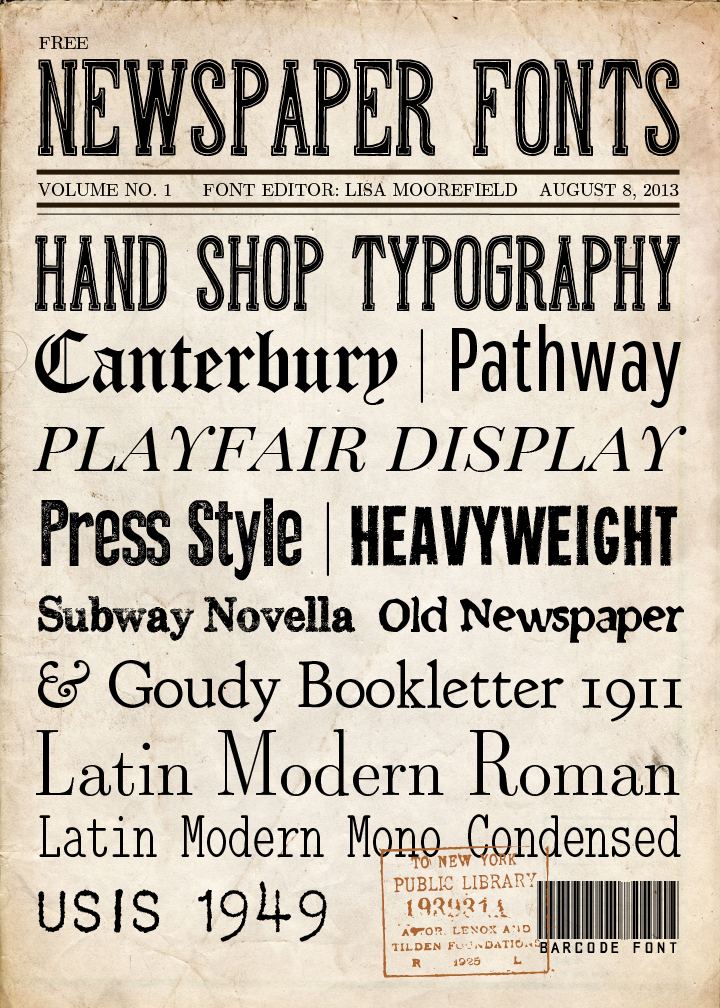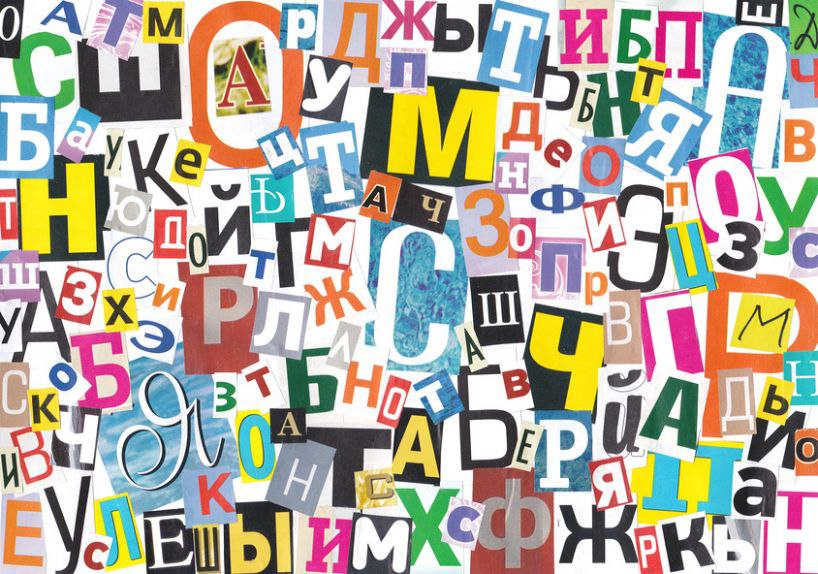
Шрифт в печатном издании | Полиграф-Сити
Г. М. Барышников, художник-шрифтовик
Даже неискушенному читателю ясно, что нельзя использовать в наборе стихотворных произведений шрифты, которыми набираются газеты или словари, а в газетах или словарных изданиях — шрифт для набора искусствоведческой литературы, так же, как в детских изданиях — шрифты для рекламы и акциденции.
Шрифт недаром считается одним из важнейших средств художественного оформления любой печатной продукции. При выборе шрифта для набора любого типа издания профессиональный издатель прежде всего учитывает его функциональные и художественно-эстетические особенности, а также удобочитаемость и психофизиологию восприятия. Один шрифт разработан специально для длительного чтения, и им набираются книги.
Другой — для энциклопедий и словарей, и ни в каком другом типе издания, в силу характера своего рисунка, расположения знака на кегельной площадке и его очка, не может быть использован.
Третий, изначально созданный для набора букварей, учебников младших классов и детской литературы, непригоден для применения в газетах или журналах.
Но всегда ли это происходит не самом деле? Наверное, каждому доводилось неоднократно сталкиваться с таким явлением, когда интересная по своему содержанию книга читается с трудом. Вы испытываете какой-то дискомфорт, с нарастающим раздражением, спотыкаясь на каждой строке, с трудом одолеваете очередную страницу и не понимаете, отчего не плучается осилить всего 10-12 страниц за раз.
Массовый читатель, не искушенный в издательском деле, не может понять, почему это происходит. Да и не всякий полиграфист сразу поймет, в чем дело. Со мной это случалось несколько раз. Впервые это произошло, когда в руки попал современный переводной роман американского писателя Роберта Сильвестра «Вторая древнейшая профессия». Обычно интересная книга читается легко, как говорится взахлеб, но в этот раз более нескольких страниц подряд осилить не удавалось.
Если бы этой гарнитурой была набрана «Барышня-крестьянка» А.С. Пушкина или «Темные аллеи» И.А. Бунина, то данный шрифт придал бы им национальный колорит и стал одним из основных средств художественного оформления этих произведений. В современном романе из жизни американских журналистов-газетчиков он воспринимался как нечто чужеродное, отрицательно влияя на восприятие его содержания.
Затем с подобным казусом пришлось столкнуться в первом издании «Путешествия на Кон-Тики» Тура Хейердала и еще в ряде других книг разных издательств. Почему же возможны такие ляпсусы? Есть, пожалуй, два объяснения такому неправомерному использованию шрифтов.
Во-первых, когда появляется новый оригинальный и привлекательный шрифт, у издателя возникает соблазн использовать его немедленно, одним из первых.
Существует еще одна причина, но совершенно иного свойства. Во времена, когда шрифтовой ассортимент, имевшийся в распоряжении издателей, был чрезвычайно беден и не предоставлял большого выбора, предпринимались попытки придать некую универсальность какому-то одному шрифту. Например, в довоенные и первые послевоенные годы (30-50 гг. ХХ века) такая искусственная универсальность была присуща
Особняком стояли две гарнитуры, имевшие жесткую привязку к определенным типам изданий. Это Обыкновенная новая гарнитура, которая была разработана в предвоенные годы специально для набора 3-го издания собрания сочинений В.
Даже в настоящее время существует какое-то странное и необъяснимое пристрастие к использованию тех или иных шрифтов у части отечественных издателей. Это можно проследить на протяжении двух-трех последних десятилетий. Так, с появлением русифицированного и модернизированного варианта гарнитуры Таймс, разработанной в начале 30-х годов прошлого века для набора лондонской газеты одноименного названия, чуть ли ни каждое второе массовое издание в нашей стране стало набираться этим шрифтом. Даже детская энциклопедия «Что такое. Кто такой» или «Приключения Карандаша и Самоделкина» Ю. Постнова для младших школьников набрано все той же Таймс.
Несколько позже возникло очередное, чуть ли ни поголовное увлечение шрифтом рубленого типа, и гарнитуры Футура и Гельветика начинают фигурировать во многих изданиях, от книг до журналов и газет. С широким внедрением в наборный процесс компьютерной техники не такая уж, за редким исключением, высокая культура шрифтового оформления печатанных изданий упала еще ниже.
Шрифт в значительной степени перестал быть одним из важнейших элементов художественного оформления полиграфической продукции и постепенно стал превращаться в заурядный носитель информации. Если во времена металлического набора появление каждой новой гарнитуры напрямую зависело от выпуска соответствующего комплекта матриц, то с переходом на современную технику и цифровое представление шрифта сложилась совершенно иная ситуация. На рынке появилось большое количество разнообразных шрифтов как отечественного, так и зарубежного производства, предоставляющих издателям широкий выбор в их использовании. И одновременно совершенно перестало действовать правило использования шрифтов применительно к конкретному типу изданий.
В связи с этим невольно хочется помянуть добрым словом отмененный с 1 июля 2003 года ГОСТ на типографские шрифты, в котором содержались рекомендации по использованию каждой гарнитуры, включенной в него, по прямому назначению. В результате это привело к тому, что все огромное количество книжной продукции, как отечественной, так и переводной, независимо от того, каким издательством выпущено то или иное произведение, отличается друг от друга только внешним оформлением, а внутри — почти полное однообразие от использования весьма ограниченного ассортимента шрифтов.
Calendas PlusЭто приятный и красивый шрифт, который можно использовать для разных задач. У него много лигатур, которые будут красиво смотреться. Попробуйте и посмотрите, как это будет выглядеть.